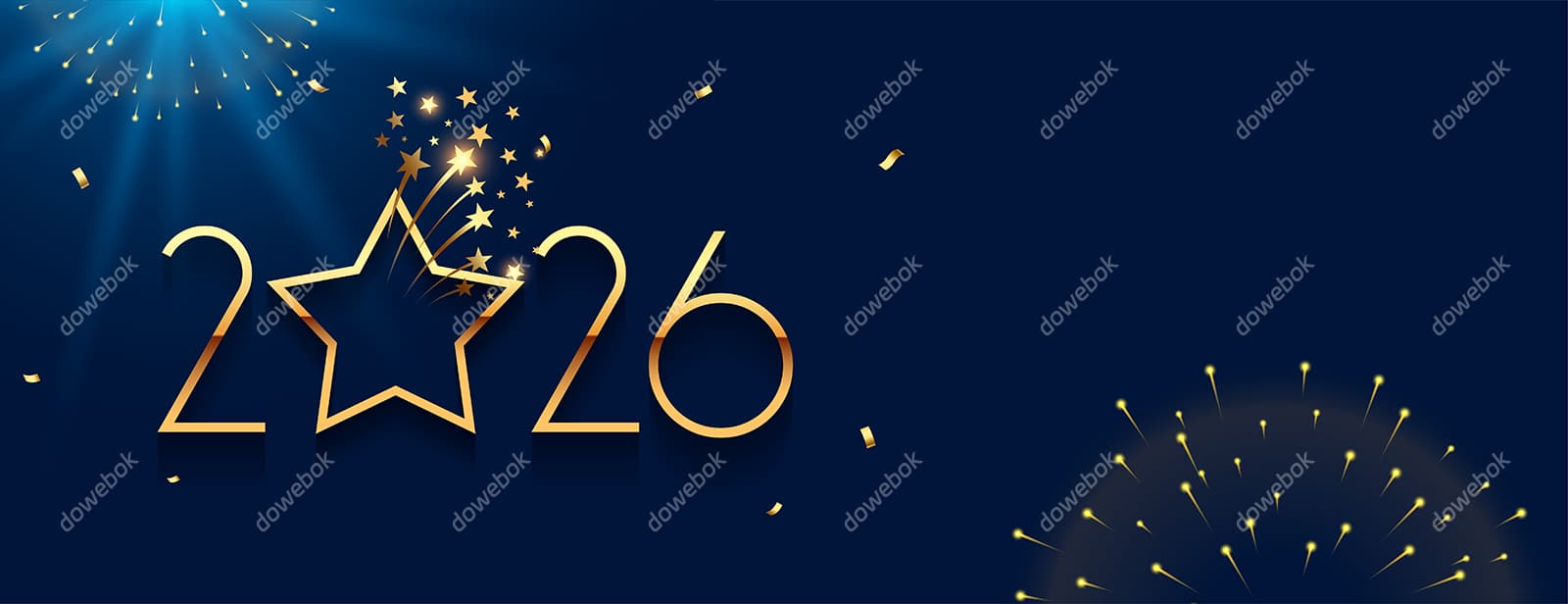
这是一款由金色星形装饰和数字设计的 2026 新年快乐 banner 矢量素材,深蓝背景上,金色 “2026” 字体间嵌着星形装饰,搭配迸溅的烟花、星芒元素,营造出热烈的庆典氛围。整体金蓝配色高级且醒目,烟花与星星的组合既传递新年的喜庆热闹,又借金属质感凸显精致感,适配新年活动海报、电子祝福素材等场景,视觉效果动感且富有节日张力。